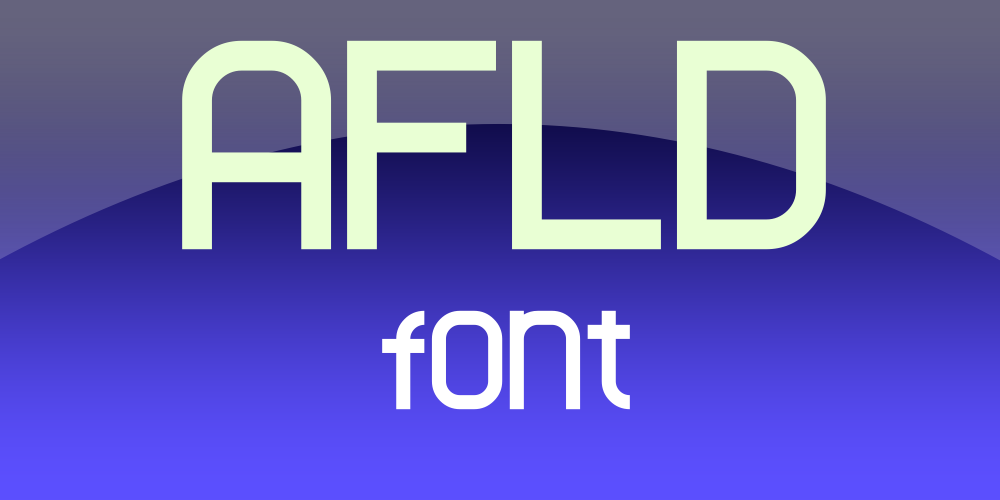
Aqui está uma descrição em português para a página de download da font ‘AFLD’, adequada aos requisitos fornecidos: É com grande entusiasmo que DLyonsFont anuncia mais um lançamento, agora com 100 novas fontes disponíveis no Befonts! Este é o centésimo espaço Fontspace font criado pelo nosso designer talentoso, Hamilton. ‘ADFLL’ não é apenas outro design da série sans-serif que você já conhece, mas uma criação que combina elegância e modernidade com um toque de originalidade. AFLD não é apenas mais uma opção entre as muitas fontes disponíveis; ela carrega consigo a assinatura distintiva do designer Hamilton. Seja em ambientes profissionais ou criativos, AFLD oferece a perfeita combinação de estilo e conforto de leitura que todos procuram nos espaços sans-serif. Com seu design fluido e elegante, AFLD é uma escolha inteligente para designers gráficos, ilustradores e até mesmo escritores. Seja para destacar o texto em um design profissional ou para dar um toque distintivo a um projeto pessoal, AFLD tem tudo para torná-lo única e inovadora. Descubra o poder da elegância na simplicidade com ADFLL – uma fonte sans-serif que você não pode deixar de experimentar.